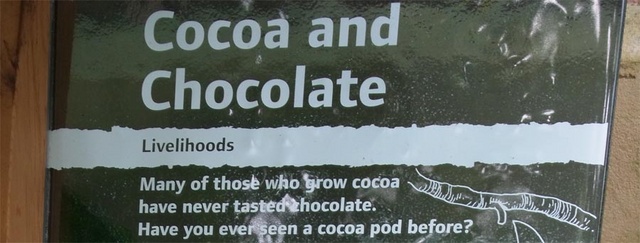
Eden Project - komme nicht drauf
Ihr seht das doch vermutlich mit einem Blick? Die Schrift wird konsistent für alle Anzeigetafeln des Eden-Projektes verwendent. Ich komme gerade nicht drauf. Whatthefont schlägt die schöne Dobra von Dinos dos Santos vor. Die ist es aber nicht; die hat ein rundes und kein kantiges e.
Ich frickele noch mal etwas herum aber ich wette jemand von Euch hier ist schneller ...
Da hätte ich auch wirklich selber drauf kommen können – wo es doch schon die Hausschrift meines vorherigen Arbeitgebers war.
@Bertel: nach einem pdf habe ich natürlich auch gesucht, bin aber irgendwie nicht fündig geworden (blind wie üblich). Woher kommt’s? Ach, und wo ich schon dabei bin (ich will heute mal faul sein dürfen!), das erinnert mich ja an den Auftritt von East Coast Rail, von denen ich irgendwann auch schon mal vergeblich ein pdf gesucht hatte, weil ich den Auftritt insgesamt recht gelungen finde. Das Logo ist wenn ich mich nicht irre in der Tasse Black von Font Bureau, aber was benutzen die für den restlichen Auftritt? Findest Du für die auch so schnell ein pdf aus dem man es einfach auslesen kann? :roll::baeh::ilovetype:
Das ging sogar recht schnell:
in der Google-Suche "pdf site:www.eastcoast.co.uk/" eingeben, dann werden eben nur pdfs auf dieser URL gesucht. Das erste Ergebnis führt zu jener Erkenntnis: